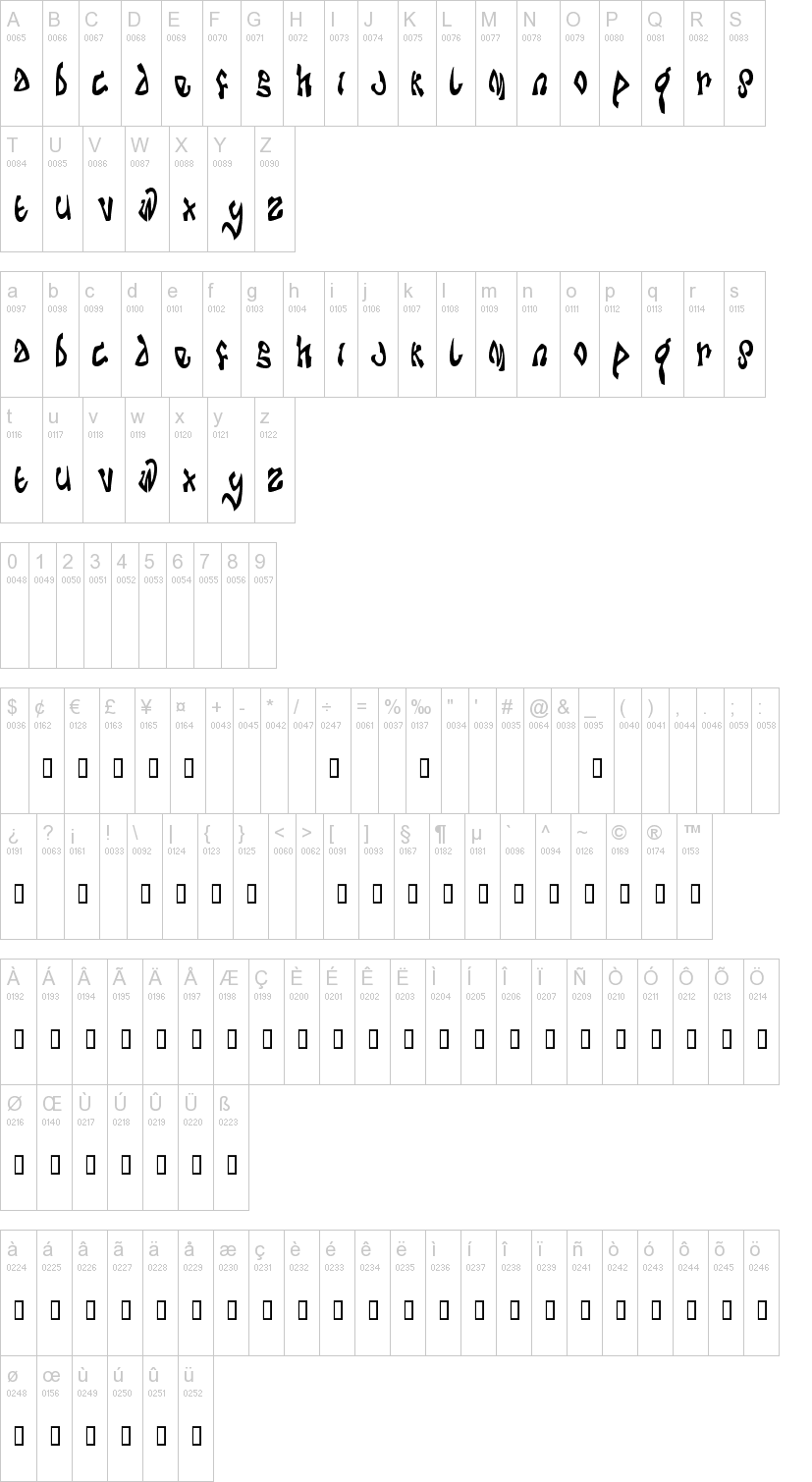
Da Bomb
Da Bomb 字体是一种非常具有冲击力和个性化的字体,它由设计师Graffiti Fonts于2002年创造。这种字体在设计上采用了涂鸦艺术的元素,具有非常明显的标志性和辨识度。它的字母形态较为简单,采用了大胆的线条和弧度,给人留下强烈的视觉印象,通常被用于设计海报、广告、标志等需要强调个性和冲击力的场合。此外,Da Bomb 字体有多种不同的版本和变体,比如Da Bomb Regular、Da Bomb 2、Da Bomb Drip等,可以满足不同设计需求。
Da Bomb是一款非常不错的手写艺术字体,具有很好的视觉感,适合于文化类的宣传设计、商业类品牌的广告和产品包装设计以及个性化文字排版等较多场景。